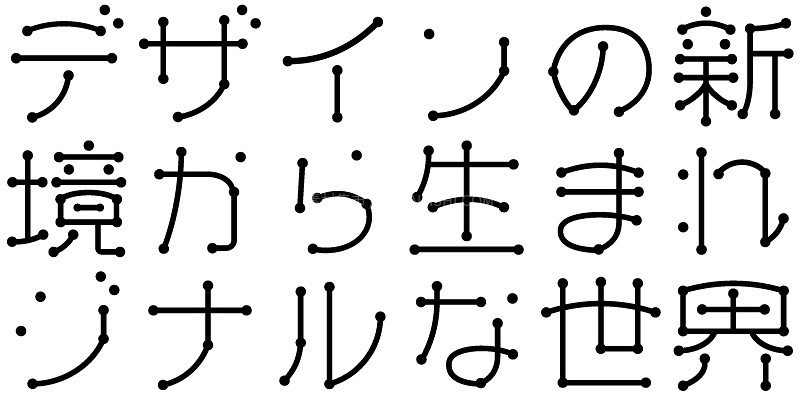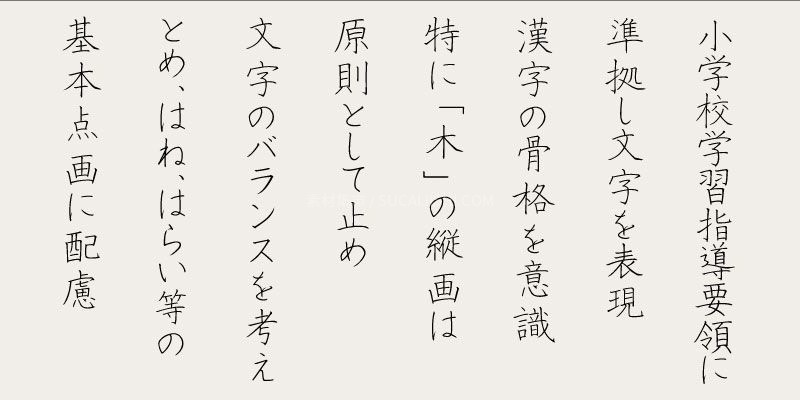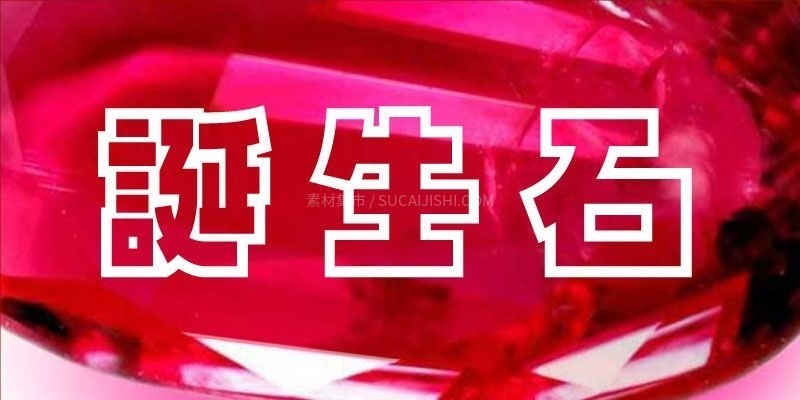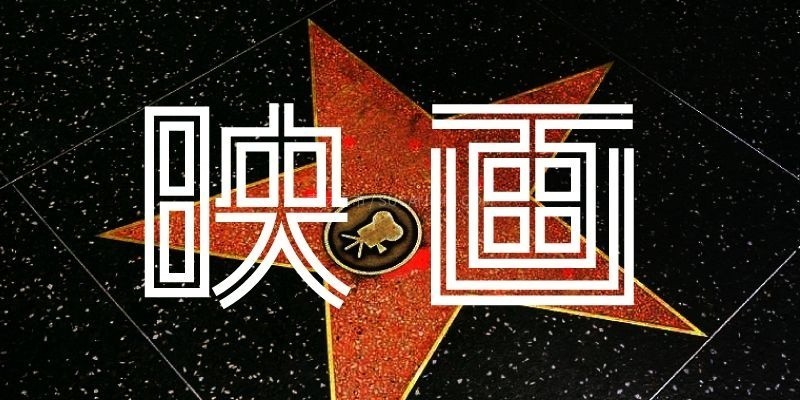
2025年上新!8款免费商用日文字体合集
2025年,全新的免费商用日文字体合集,素材君整理了 8 款高质量日文字体,涵盖教育、书法、装饰和彩色等多种风格,满足您在不同设计场景下的需求。
AB-アクセント
一款独特有趣的字体,其字母上装饰有可爱的圆圈和饰物,营造出轻松活泼的氛围。这款字体非常适合用于字幕、社交媒体帖子和流行音乐相关的设计。
AB-あらじ Kna
一款充满力量感的书法日文字体。它以有力的笔触为最大特点,每一个字形都仿佛蕴含着笔墨的张力,能为您的设计带来独特的艺术表现力。
AB-優筆楷書
一款充满优雅感的书法日文字体。它以优雅的笔触为最大特点,每一个字形都仿佛由娴熟的笔锋写就,能为您的设计带来独特的精致美学。
AH白洲学校ペン楷書体
一款专为教育领域设计的日语字体。它以模拟钢笔书写的楷书风格为特点,笔画干净利落,字形工整标准。这使得它在教学材料中表现出色,无论是在印刷品还是屏幕上,都能确保文本的清晰易读。
Moolong Candle Variable
一款独具魅力的日文字体,将可变字体技术与多彩风格完美结合。
Moolong ペイント
一款极具艺术感的日文字体,以其独特的液态风格为最大亮点。这种设计赋予字体一种流动、动态且富有创意的视觉效果,能为您的设计带来独特的视觉冲击力。
メガG-pop
一款视觉冲击力十足的日文字体,以其独特的轮廓边框风格为最大亮点。这种设计使得字形边缘鲜明,非常醒目,能为您的设计带来强烈的存在感,尤其适合需要突出显示的标题和装饰性文字。
ロゴナTwin
一款极具个性的日文字体,以其独有的双重线条风格为最大亮点。这种设计赋予字体一种现代、时尚或具有未来感(取决于具体设计)的视觉效果。